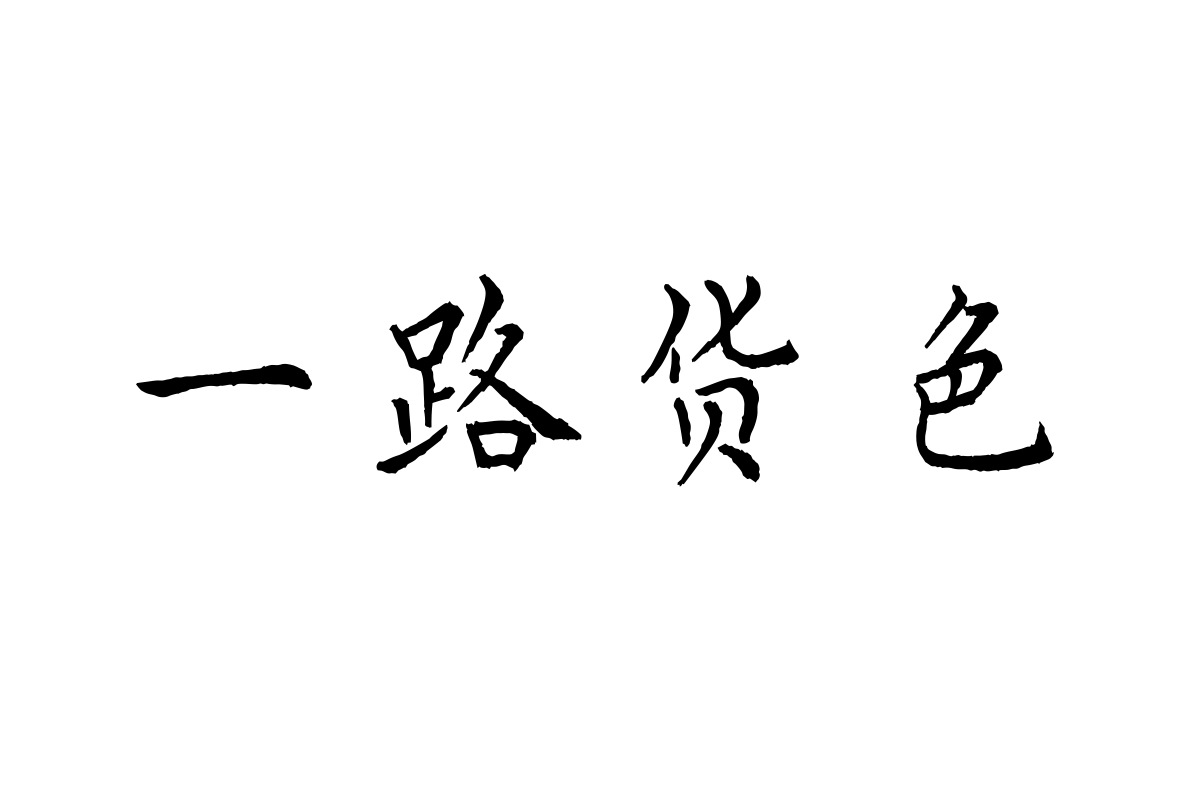
汉仪启笛小楷是一款具有独特魅力的字体。它采用了独特的笔画风格,使得每个字母都显得格外醒目和独特。这种独特的笔画风格使得每个字母都显得格外醒目和独特。
该字体的设计灵感来源于中国传统书法的笔触,通过精细的处理,使得每个字符都呈现出一种流畅而优雅的感觉。它的笔画粗细不一,既有粗犷的线条,也有细腻的曲线,给人一种既现代又古典的感觉。
此外,汉仪启笛小楷还注重字形的平衡与和谐,使得整个字体看起来既整齐又美观。无论是在正式的文件还是在日常的书写中,都能展现出其独特的魅力。
总的来说,汉仪启笛小楷是一款极具个性和艺术感的字体,无论是对于设计师还是普通用户来说,都是一个值得尝试的选择。